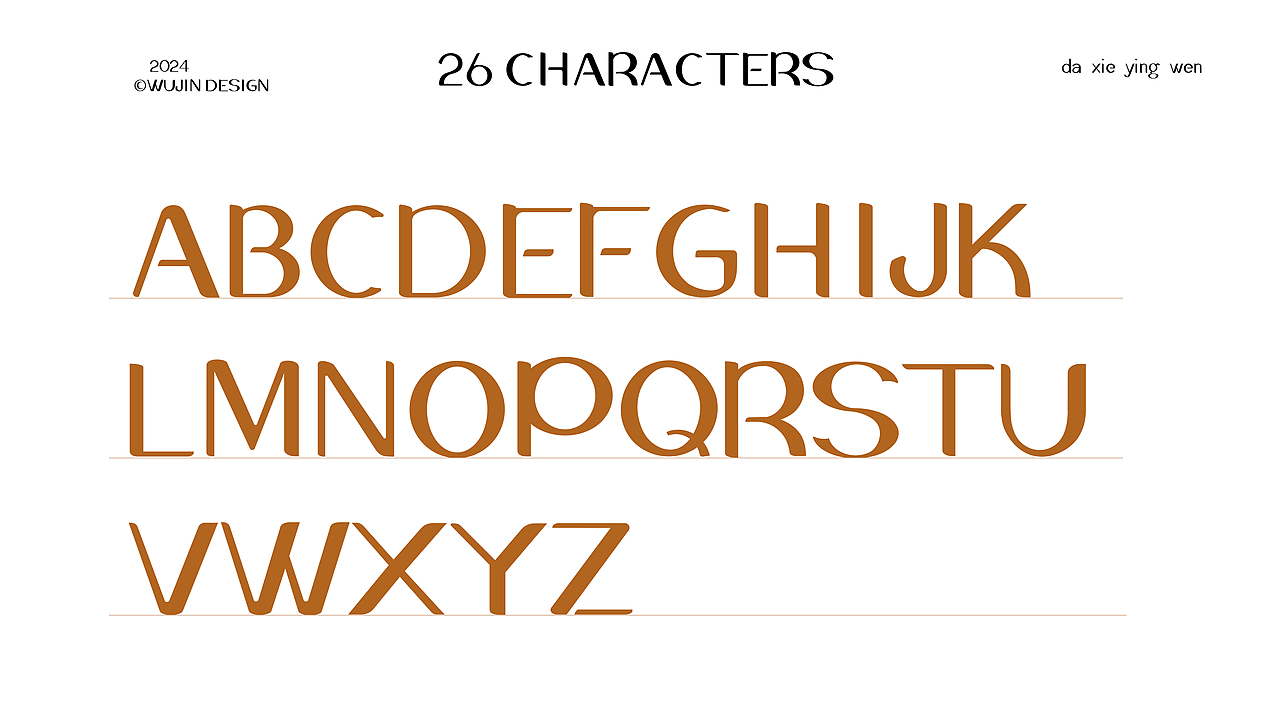
这款字体灵感源于普拉提的动作,将练习普拉提时身体的流畅动作和优雅线条融入字体设计中。以海豚为例,某些普拉提动作模仿了海豚的优雅姿态,因此字体的尾部设计得较为圆滑,以展现鲸鱼般流畅的线条。
这款字体适用于瑜伽、美妆等相关领域的文案和设计,能够为作品增添一份独特的艺术气息和普拉提精神。通过这款字体,希望能够让更多的人了解并感受到普拉提的魅力,从而更好地关照自己的身体和心灵。
大写英文字符
小写英文字符
阿拉伯数字
中文标点
英文标点
货币符号
数学运算符号
特殊符号